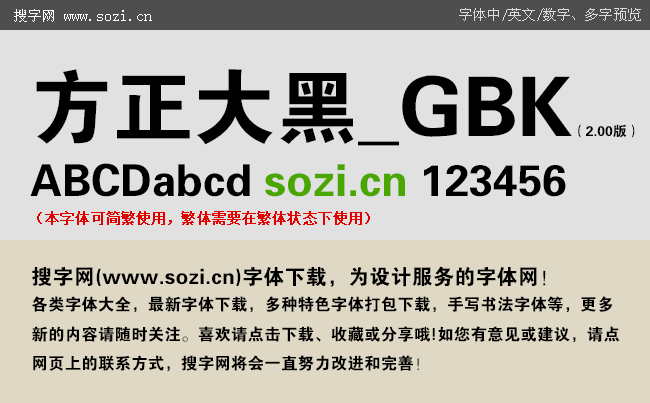
方正大黑_GBK
搜字網(wǎng)提供一款方正大黑_GBK中文字體下載,方正大黑是一款非常端正的中文字體,該字體簡潔大方,端正醒目,GBK編碼收錄文字更全,適合在正式的場合來進行使用,適合應(yīng)用于廣告設(shè)計、名片設(shè)計、包裝印刷、產(chǎn)品設(shè)計等應(yīng)用。